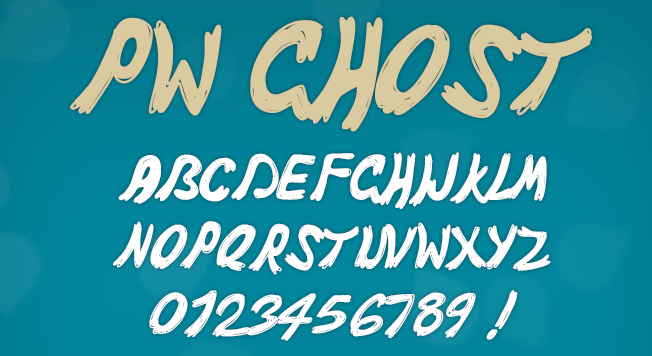
PW Ghost est une typo cartoon, un peu rétro aussi bien sympathique. A utiliser en priorité pour des gros titres, ou des posters ! Le set comprend les lettres majuscules et les chiffres, et vous pourrez l'utiliser à titre gratuit pour un usage personnel. Pour un usage commercial ou la conception de caractères manquants, merci de me contacter.